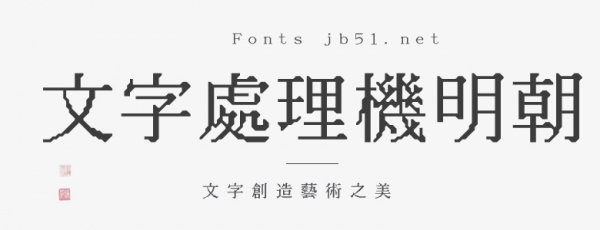
文字處理機明朝(日文名:ワープロ明朝)是一種復(fù)制1980年代和1990年代初在文字處理機上使用的位圖字體放大過程的字體。
在文字處理機的后期,安裝了大綱字體以實現(xiàn)漂亮的放大,但在此之前,位圖字體是在打印大字符時放大的。 在此之前,位圖字體被用來放大大字符進(jìn)行印刷。
文字處理機明朝是一種24點的Mincho位圖字體,即jiskan24,它經(jīng)過這種插值處理,形成了一種輪廓字體。